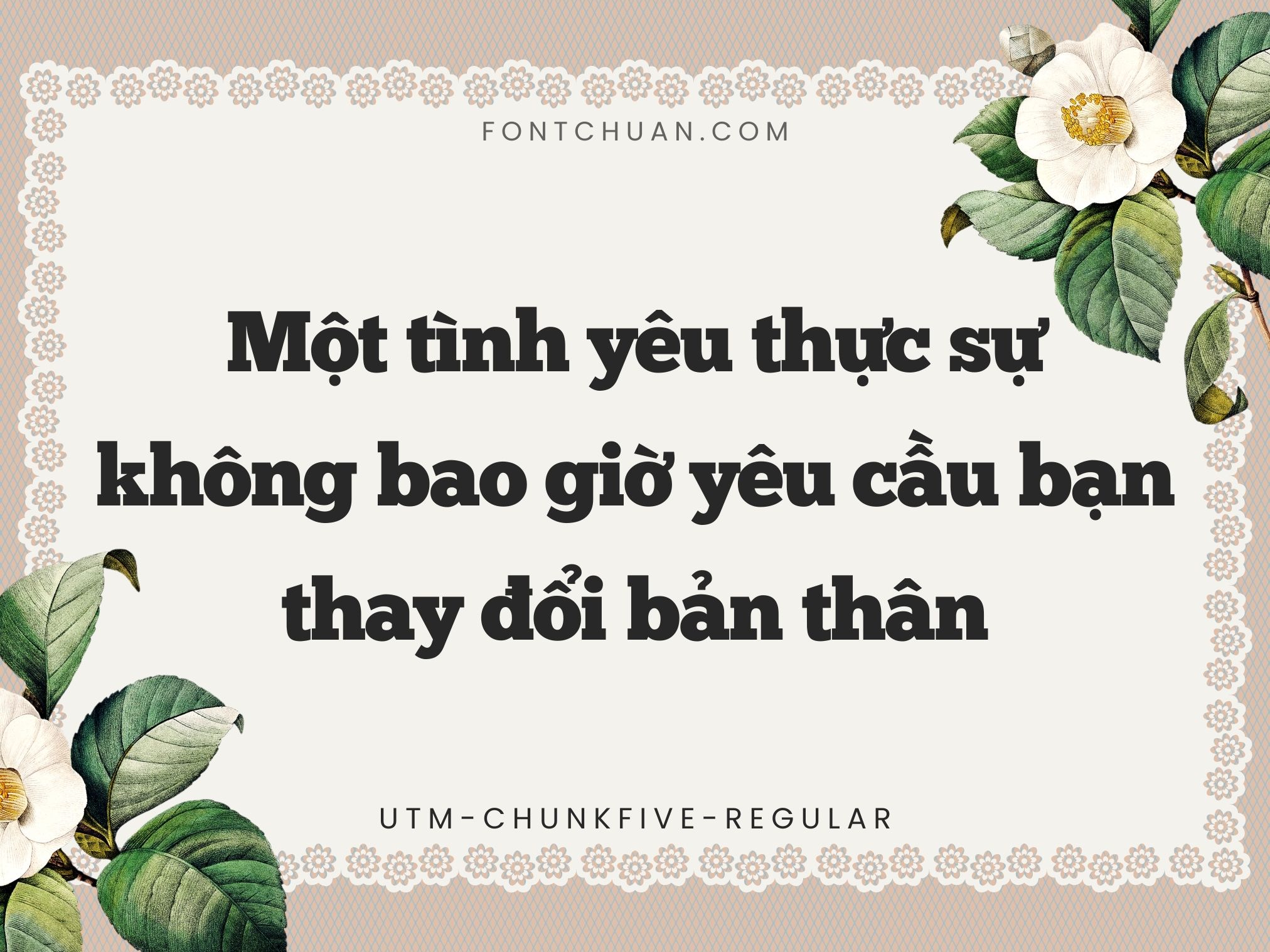
Font UTM Chunkfive Việt Hóa
UTM ChunkFive Regular là phiên bản Việt hóa của font chữ ChunkFive, cũng là Font Slab Serif đậm được thiết kế bởi The League of Moveable Type. Font này nổi bật với các ký tự có đường nét dày và chắc chắn, gợi nhớ đến phong cách chữ in trên các tiêu đề báo chí và áp phích cổ điển của Mỹ. Phiên bản Việt hóa đã được thực hiện bởi Unicode Thiên Minh, hỗ trợ đầy đủ tiếng Việt cùng hơn 100 ngôn ngữ khác. Đây là một trong những font được cộng đồng thiết kế sưu tầm và chọn lọc nhằm đáp ứng nhu cầu đa dạng trong thiết kế.
UTM ChunkFive Regular có cấu trúc chữ với các nét dày và chân chữ rõ ràng, tạo nên sự mạnh mẽ và thu hút. Font này phù hợp cho các ứng dụng như thiết kế tiêu đề, logo, biển hiệu và các ấn phẩm in ấn yêu cầu sự nổi bật và ấn tượng. Các ngành nghề như quảng cáo, giáo dục, công nghệ và bất động sản có thể tận dụng UTM ChunkFive Regular để tạo điểm nhấn độc đáo trong thiết kế.